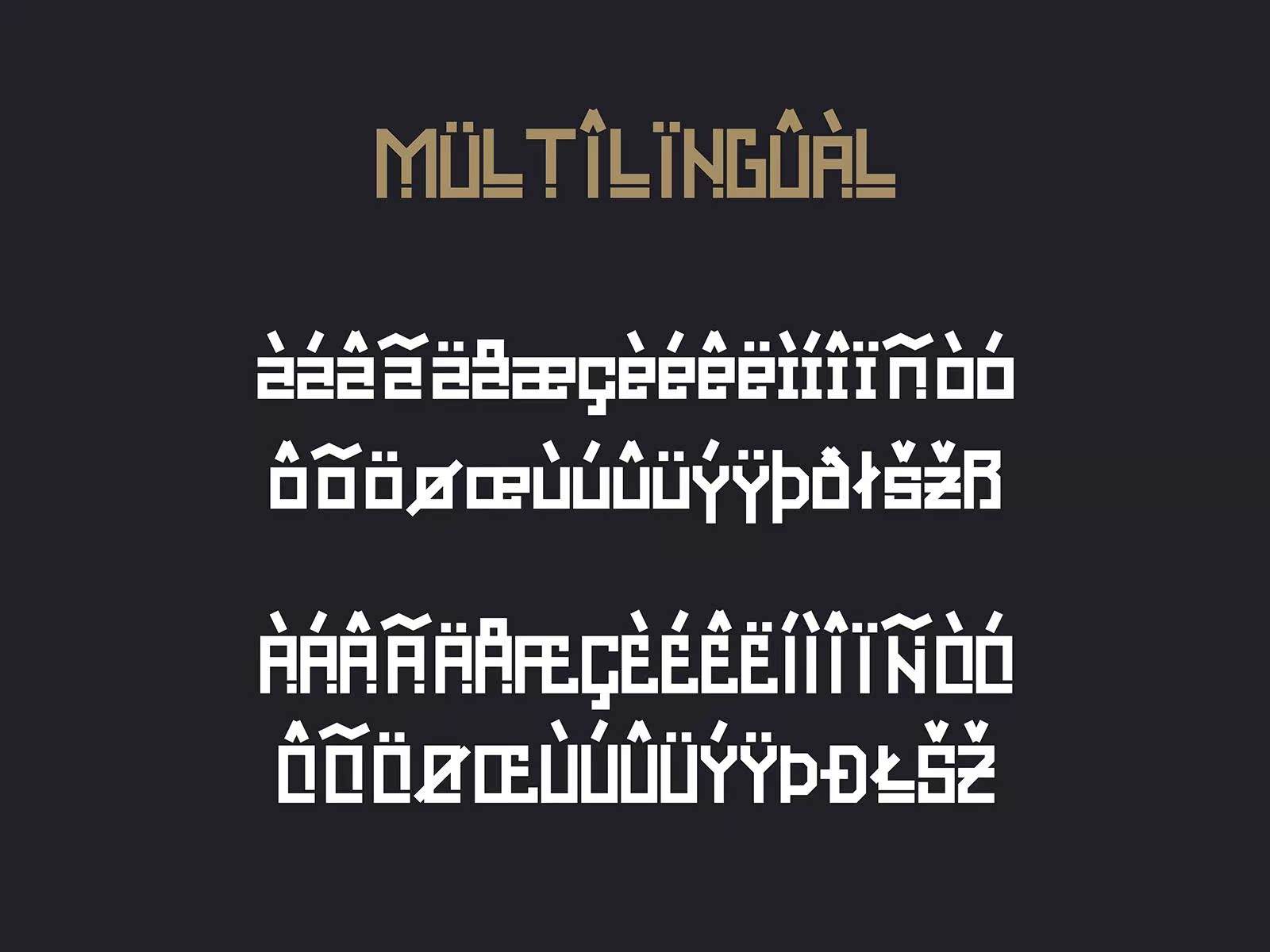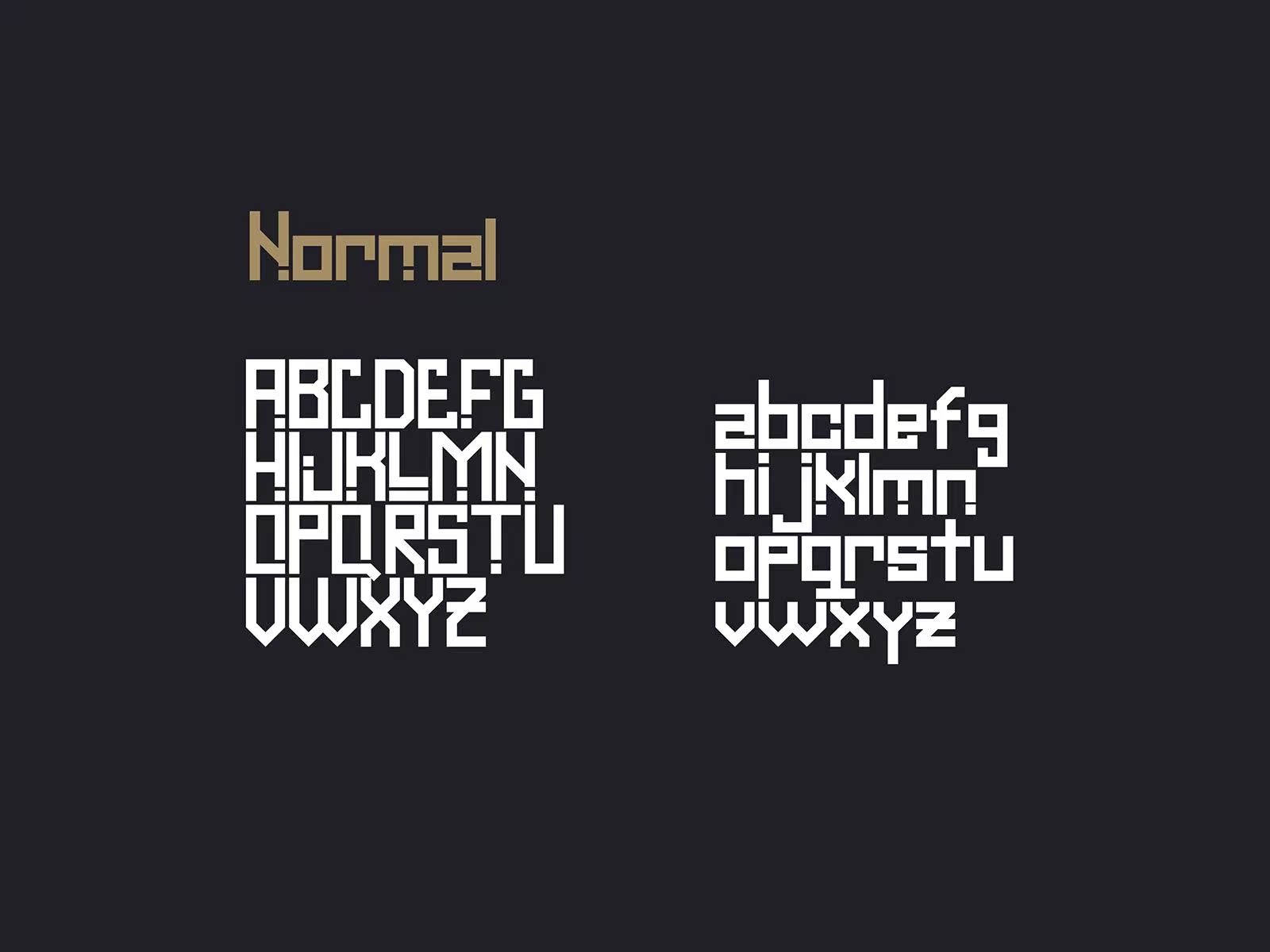
LateLoi不包含Aphiellat、sharp、Modernelegant Feel字符集。要创建美丽的组合,只需将大小写混合,即可使用可选的设计、连字、样式集和多语言。LateLoi不包含埃及象形文字。LateLoi不包含Aphiellat、sharp、Modernelegant Feel字符集。要创建美丽的组合,只需将大小写混合在一起,就可以使用交替设计、连字、文体设置和多种语言。最新版本来自埃及象形文字。